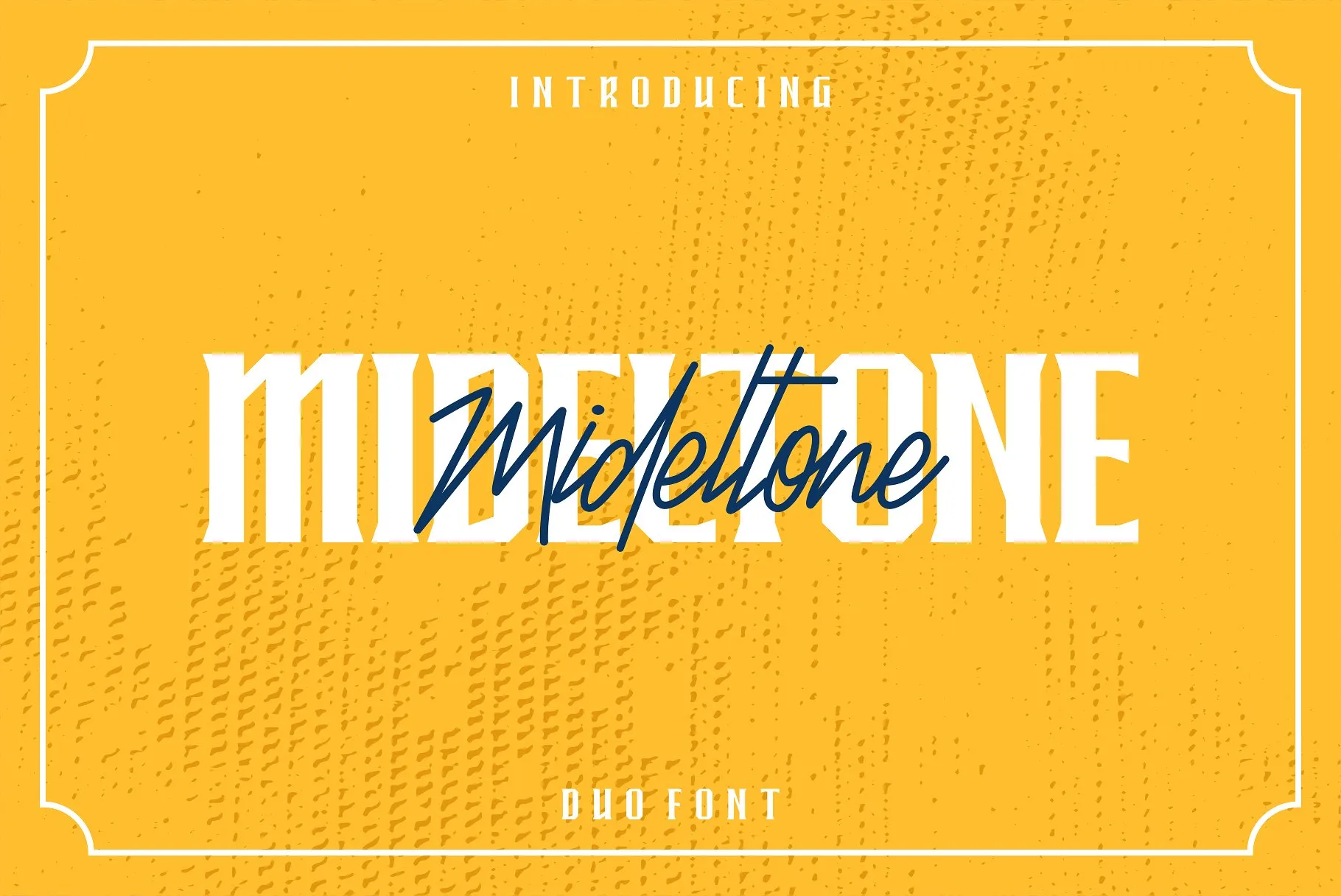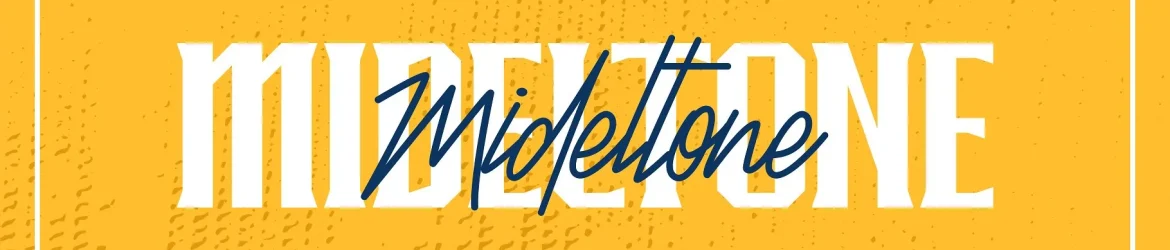
Bem-vindo à página de download para a fonte Mideltone Duo do C00zona. Esta elegante parceria de duas fontes foi criada com objetivos inspiradores, unificando uma combinação única e fascinante de tendências na tipografia. As “Mideltone Duo” foram projetadas especificamente para levar ambas as linhas elegantes das serifas modernas e caprichosas scripts cheios de personalidade em um pacote de design único e envolvente. Esta font é perfeitamente adequada para criar logos memoráveis, estilizar carteirinhas de produtos com graciosidade, incorporar citações com estilo em suas criações e até mesmo decorar posters. Ela oferece uma variedade impressionante de aplicabilidades que irão tornar seus projetos ainda mais atraentes e profissionais. Experimente Mideltone Duo para adicionar uma nova dimensão ao seu design, seja na forma de um design gráfico sofisticado ou uma frase marcante em sua próxima criação visual.